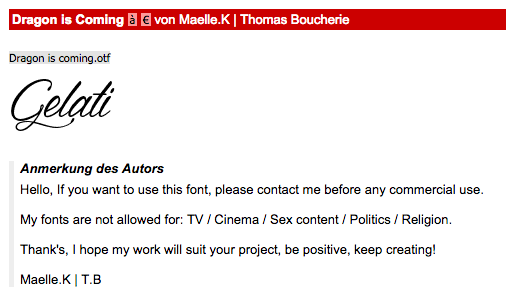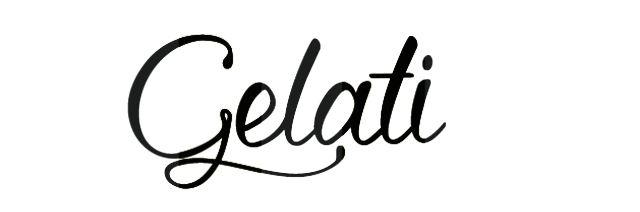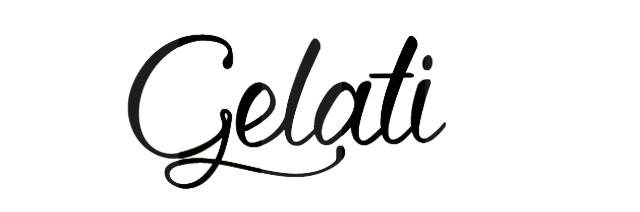
Suche Schriftart von angehängtem Foto
Ich suche eine Schriftart, welche mir weder what the font, noch what font is ausspucken konnte. Allerdings habe ich über die google Bilder Suche noch ein Logo gefunden welches die gleiche Schriftart zu verwenden schein. Könnte mir da vielleicht jemand helfen?
"Dragon is coming", in die Vertikale verzerrt.